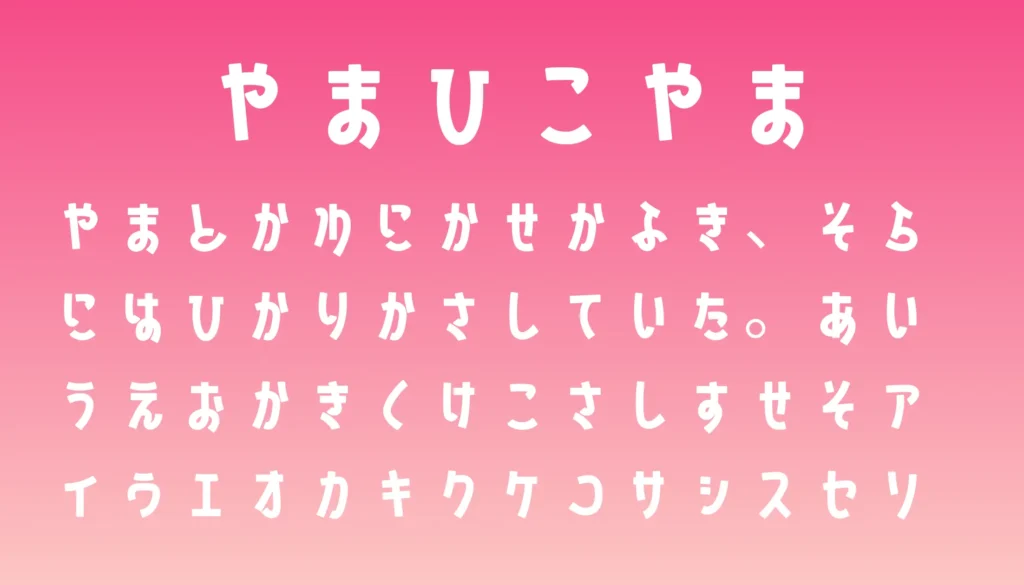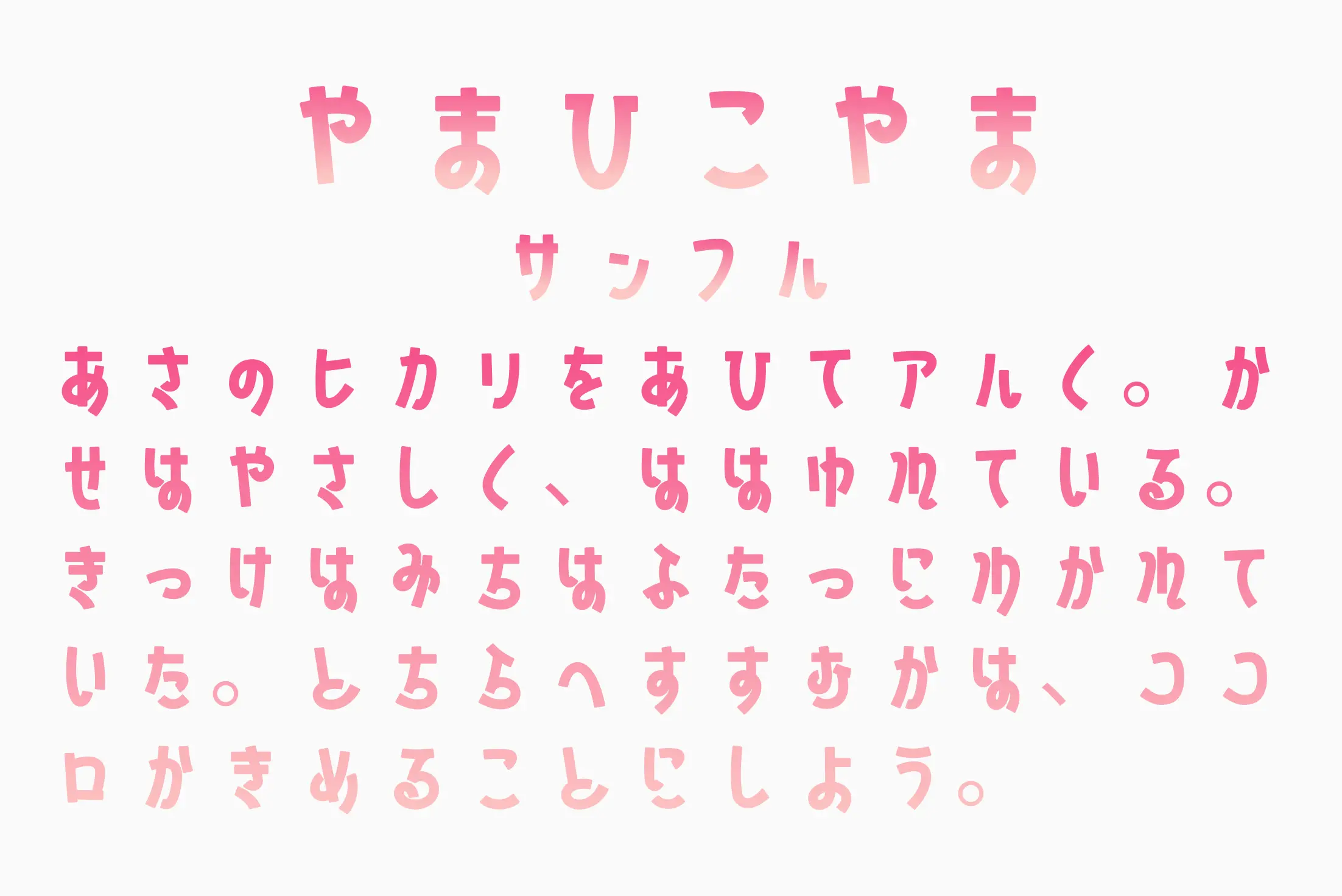
やわらかく親しみやすい字形が魅力の日本語ディスプレイフォントです。少しだけゆらぎのある形と、ころんとした丸みのあるフォルムで、明るくやさしい印象を演出できます。かわいい見出しやアイキャッチ、子ども向けデザイン、ポップなサムネイル、ショップロゴなどにぴったり。主張はあるけれど圧が強すぎないので、ナチュラルで親しみやすい雰囲気を出したいデザインに使いやすいフォントです。
山びこやま